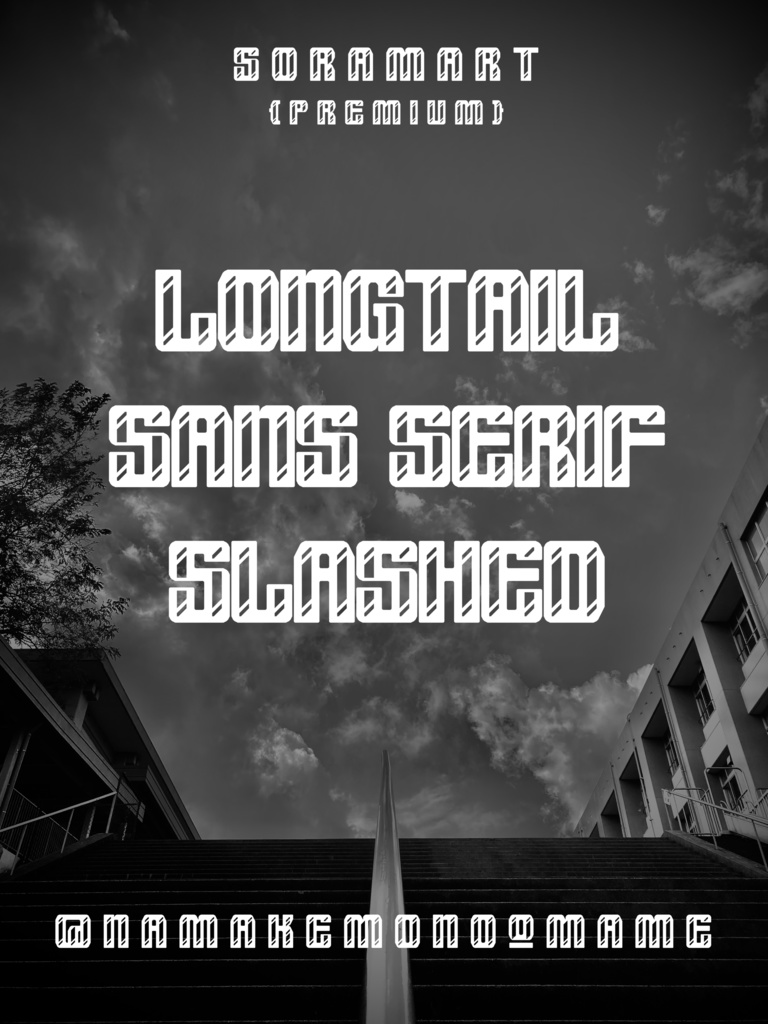
そらマートフォントデータ”Longtail Sans Serif Slashed”ダウンロード商品¥ 2,500カートに入れるギフトとして贈る「ギフトとして贈る」とはシンプルなスタイルのあしなが縦長フォントに斜線シルエットの色抜き装飾を施した "Longtail Sans Serif Slashed" です。 「TrueTypeフォントファイル」という形式です。 ダウンロードした後、Zipファイル内のデータをインストールしてお使いください。 このフォントは商用利用可となっております。 お客様の制作・創作活動のお役に立てれば幸いです。 ※使用上の注意事項などは、添付のReadmeをお読みください。 ※このフォントは有料販売専用商品です。そらマートFANBOX開設中フォント・書体フォントデータ”Crushed Can Serif Empty”そらマート¥ 2,500フォント・書体フォントデータ”Crushed Can Serif Wide”そらマート¥ 0フォント・書体フォントデータ”Crushed Can Serif”そらマート¥ 0フォント・書体フォントデータ”Dolce Cube Tall”そらマート¥ 2,500フォント・書体フォントデータ”Dolce Cube”そらマート¥ 2,500フォント・書体フォントデータ”Eight-bit Quest Wide”そらマート¥ 2,500フォント・書体フォントデータ”Eight-bit Quest”そらマート¥ 2,500フォント・書体フォントデータ”Tonik Crate”そらマート¥ 2,500フォント・書体フォントデータ”Vapor Sprout Edge”そらマート¥ 2,500フォント・書体フォントデータ”Vapor Sprout Wide”そらマート¥ 2,500フォント・書体フォントデータ”Vapor Sprout”そらマート¥ 2,500フォント・書体フォントデータ”Star Shoot Ray”そらマート¥ 2,500フォント・書体フォントデータ”Star Shoot Black Wide”そらマート¥ 2,500フォント・書体フォントデータ”Star Shoot Black”そらマート¥ 2,500フォント・書体フォントデータ”Mars Invader Balloon”そらマート¥ 2,500フォント・書体フォントデータ”Mars Invader Wide”そらマート¥ 2,500フォント・書体フォントデータ”Mars Invader”そらマート¥ 2,500フォント・書体フォントデータ”Rock Cut Serif”そらマート¥ 2,500フォント・書体フォントデータ”Rock Cut Drop Wide”そらマート¥ 2,500フォント・書体フォントデータ”Rock Cut Drop”そらマート¥ 2,500もっと見る